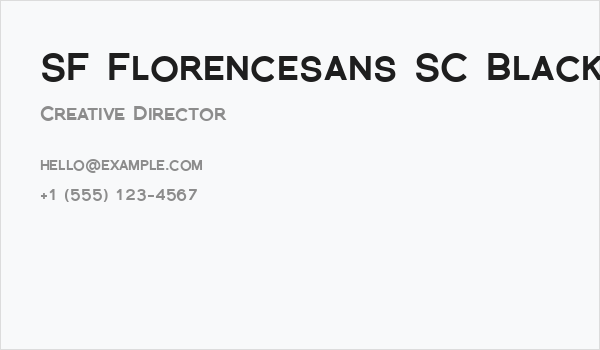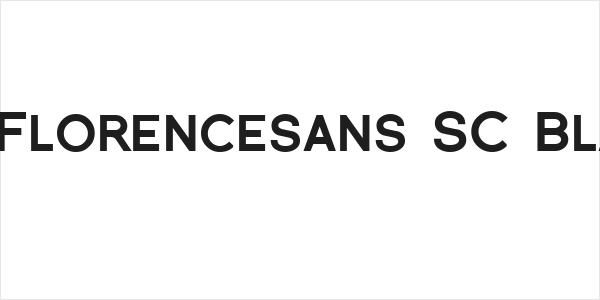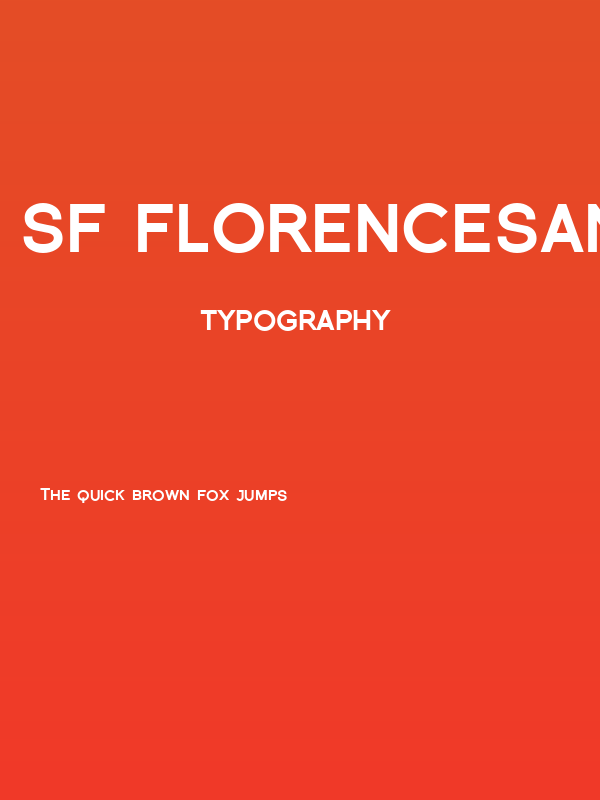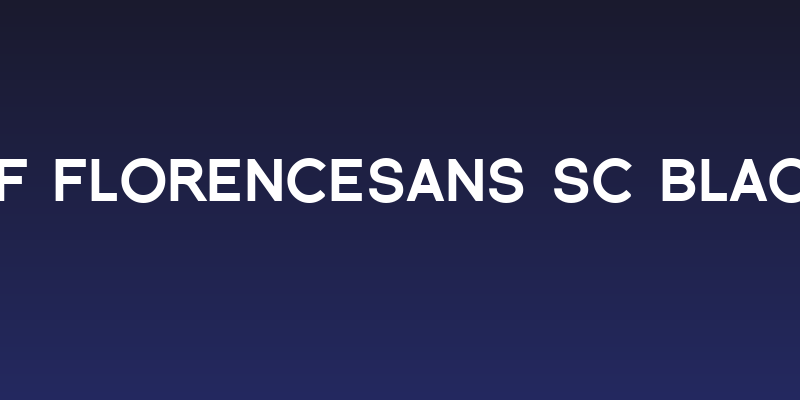
SF Florencesans SC Black Font
| Caz de utilizare | Headlines, Logos, Branding |
| Proiecte propuse | Ideal for branding, advertising, headlines, and digital media where a strong, modern presence is required. |